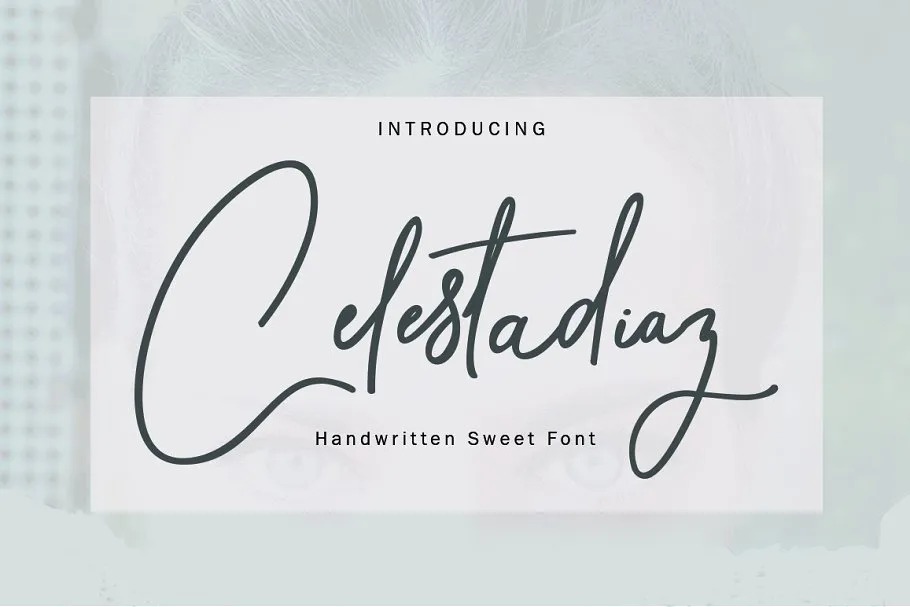
Celesta diaz Script Font – Download Grátis
Celesta diaz é uma nova fonte feita a mão, com um tom suave e perfeita para designers profissionais adicionarem um toque elegante à sua próxima criação visual. Trata-se de uma fonte de calligrafia moderna que incorpora o estilo atual da escrita a mão, perfeitamente adequada para diversas finalidades gráficas como branding, cartões de convite para casamentos, revistas, mugs, cartas de negócios, citações e anúncios. Esta fonte atinge perfeitamente os requisitos de uma nova opção de fontes de calligrafia feita a mão para designers, oferecendo flexibilidade e estilo para um amplo leque de tarefas. Quer seja para dar um toque refinado em cartões de negócios ou criar artigos memoráveis para seu próximo projeto editorial, Celesta diaz proporciona uma escolha de qualidade que fará a diferença na sua produção visual. Aproveite primeiro e veja como esta fonte modernizada pode moldar seu trabalho de design.